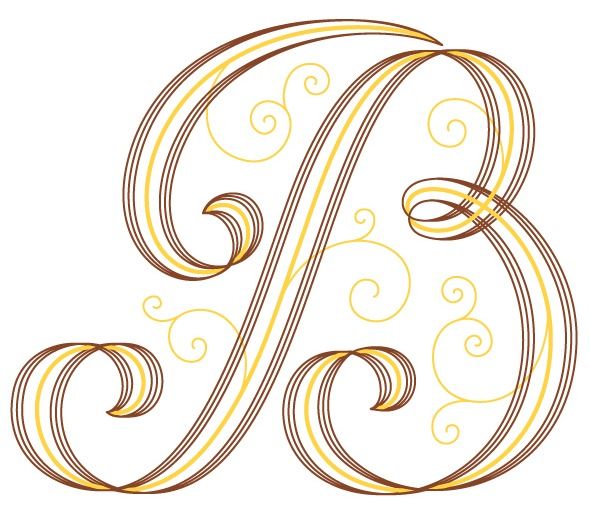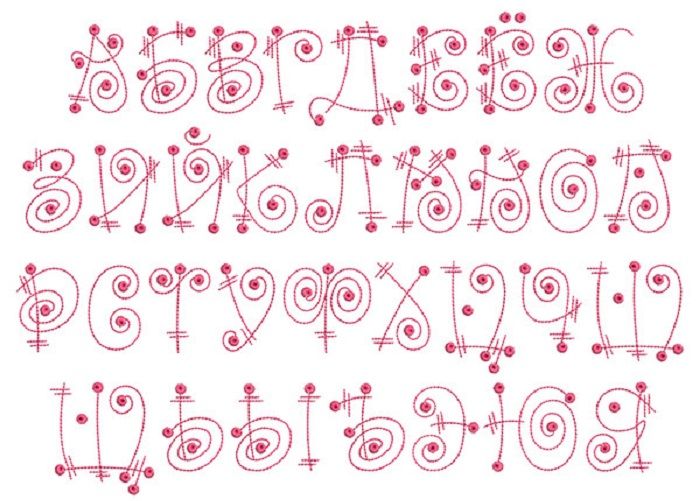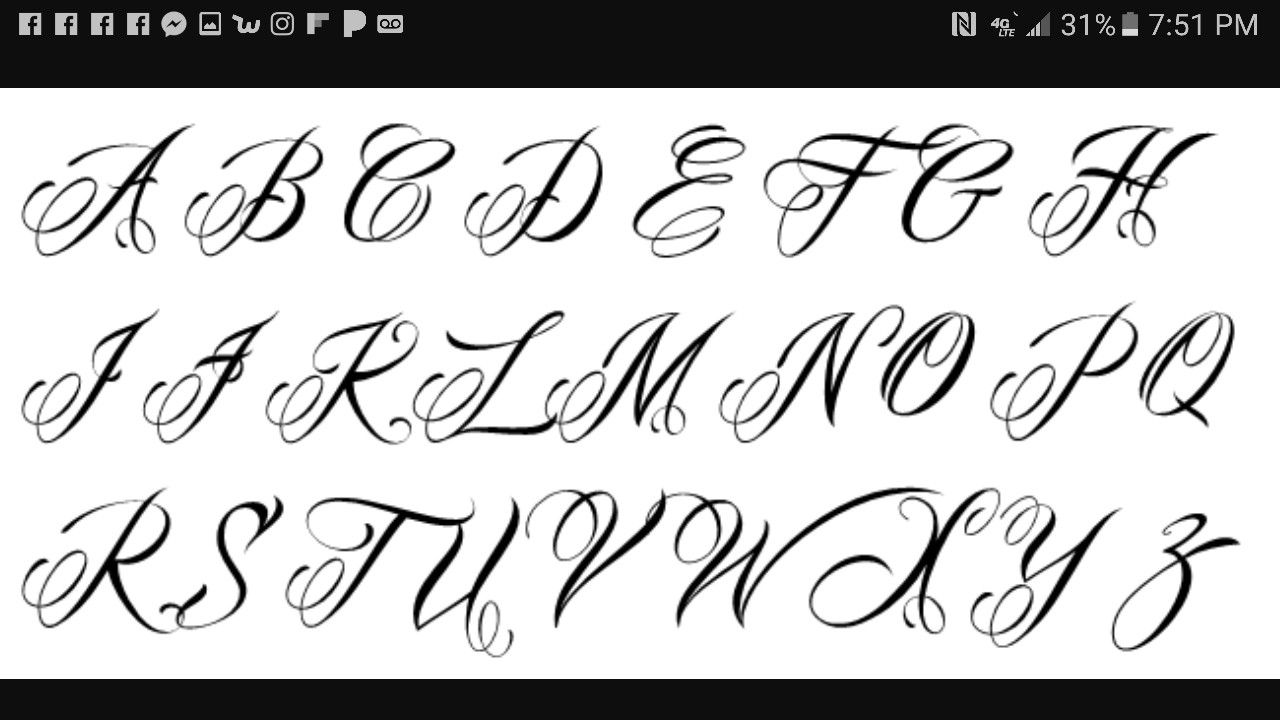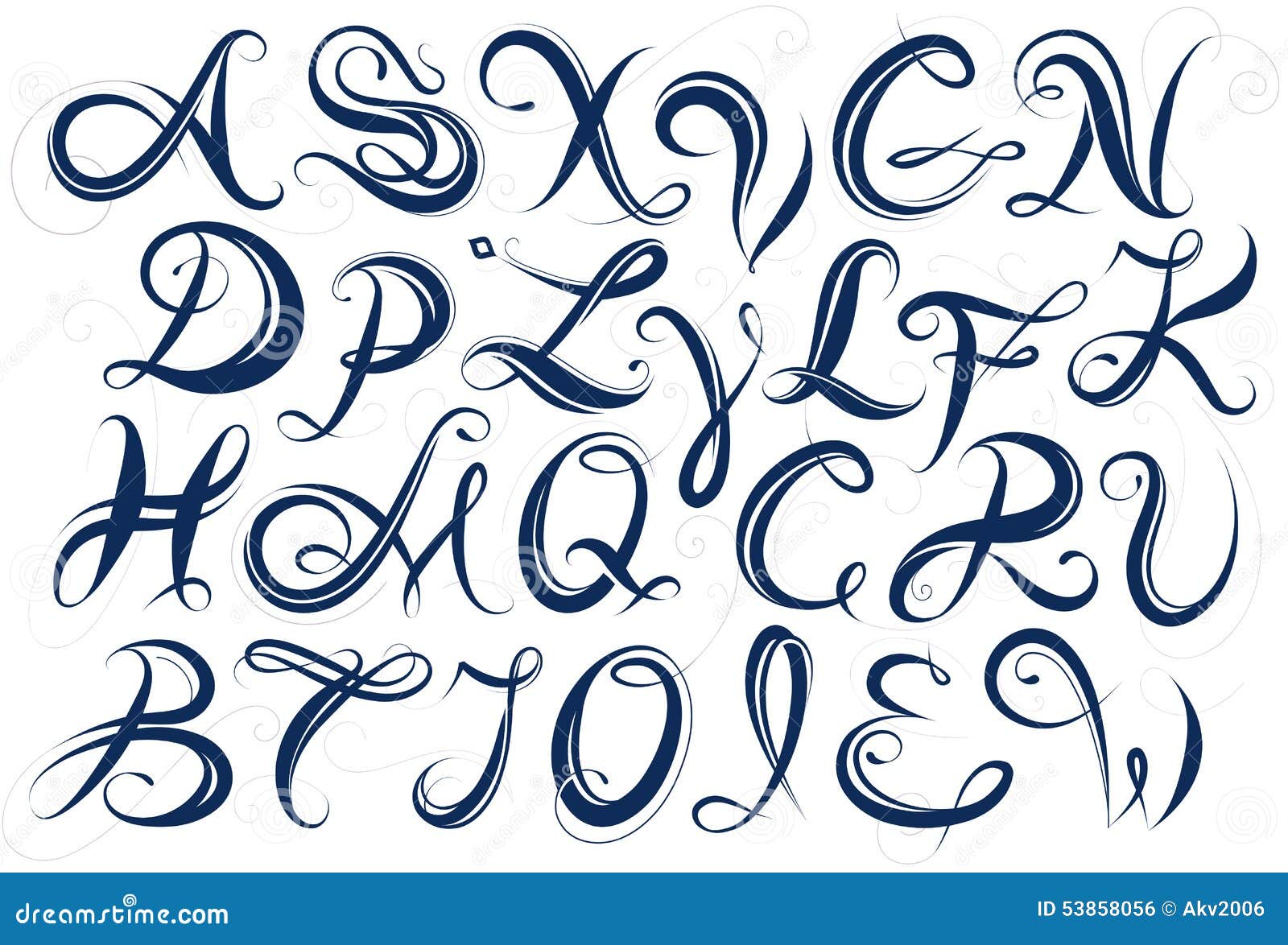
ИСКУССТВО ПЕРВОЙ БУКВЫ | Наука и жизнь
Книжный термин «инициал» происходит от латинского слова «initialis», что в переводе означает «начальный». Так называют заглавную букву увеличенного размера, с которой начинается текст книги, главы или отдельный абзац. В русской традиции инициал чаще всего именуют буквицей. Буквица может быть шрифтовой или декорированной, одноцветной или красочной, но, как бы она ни была исполнена, первое и главное её назначение — привлечь внимание читателя к началу текста. Графически буквица напоминает птичье гнездо в кроне дерева весенней порой — даже издалека глаз легко различает его в сплетении ветвей. И как гнездо украшает и оживляет дерево, так и инициальная буква украшает и оживляет собой начальную страницу. Это второе и, пожалуй, не менее важное свойство инициала: выполненный со вкусом и тактом, он радует глаз.Наука и жизнь // Иллюстрации
ПЕРОМ И КИСТЬЮ
История украшения начальных букв насчитывает более полутора тысяч лет.
Самые древние
инициалы обнаружены в античной рукописи сочинений Вергилия конца IV — начала V
века, от которой сохранились считанные листы. Большие красочные литеры в начале
каждой страницы художник составил из геометрических фигур наподобие мозаики.
Едва ли до нас дошёл первый опыт подобного рода. В названные века, видимо, уже бытовала традиция выделять начало текста, создавая торжественное вступление в книгу. Однако листать календарь назад, отодвигая дату рождения инициала в глубь веков, особой причины нет. Он появился в книге именно тогда, когда и следовало ему появиться — на излёте античности, в преддверии грядущего Средневековья. Одна великая эпоха сменялась другой: уходило в прошлое слово звучащее, искусство ораторов и певцов-аэдов — наступали, по словам С. С. Аверинцева, «времена писцов как хранителей культуры и Писания как ориентира жизни… времена трепетного преклонения перед святыней пергамена и букв».
В те годы книга уже приняла форму кодекса — стопки сшитых друг с другом тетрадей.
Их изготавливали из тщательно выделанной кожи — пергамена, который пришёл на смену ломкому папирусу. Он и служил много дольше папируса, и краски впитывал хорошо, а допущенную в слове или рисунке ошибку легко было исправить, соскоблив её ножичком.
Дойдя до последней страницы, скриптор (лат. scriptor — писец) возвращался в начало рукописи, окунал тростниковое перо в рожок с цветными чернилами и «с любовью и тщанием» вносил в начало текстовых столбцов пропущенные им заглавные буквы. Их начертание он копировал с книги, служившей ему образцом, или полагался на собственный талант каллиграфа. Позднее эту работу — прорисовку и расцвечивание инициалов и вписывание заголовков (рубрик) — в книжных мастерских стали выполнять особые художники: иллюминатор (от лат. illumino — украшаю) и рубрикатор (от лат. ruber — красный).
Чаще других для украшения чёрного текста употреблялись именно красные чернила, так называемый миний (латинское название сурика). Это несложное сочетание цветов нередко используется и ныне.
С красным цветом, кстати, связано и раннее название инициала —миниатюра, переводимое как «рисованный минием». Пройдут столетия, прежде чем это слово станет обозначать любое живописное изображение малого размера и тонкой работы.
Помимо красной в обиходе античных и средневековых писцов имелись синяя, жёлтая и зелёная краски, богатые оттенками. Для письма по цветному фону применялись белила. В роскошных манускриптах на исполнение инициалов шло творёное (растёртое в порошок) золото, реже — серебро. С благой целью сделать книгу дешевле сочинялись многочисленные рецепты для замены драгоценных металлов: толкли мелко-намелко хрусталь, ртуть смешивали с уксусом, рыбьим клеем и тальком… Однако со временем такой суррогат обесцвечивался или, что ещё печальней, проедал пергаменную страницу насквозь.
В целом же краски дошедших до нас инициалов и по сей день полны нежности и света, словно нанесены они не столетия назад. Завидная их сохранность объясняется тем, что большую часть времени книги пребывали в закрытом и даже застёгнутом виде, страницы были недоступны солнечным лучам и пыли, а чтобы пергамен не грызли мыши, писцы добавляли в чернила полынную настойку.
Заглавные буквы в начале текста, на первых порах просто выделяемые цветом, от книги к книге росли в размерах, выступали за край строки, украшались плетением и фигурками животных. Неискушённому взгляду может показаться, что персонажи этих рисунков случайны и внесены художником в текст для забавы — настолько они порой далеки от его содержания. Но на деле средневековый мастер уделял смыслу нисколько не меньше внимания, чем, скажем, цветовому равновесию или композиционной завершённости своей работы.
Для убранства ранних европейских книг характерно обилие христианских символов, ныне достаточно подзабытых.
Для читателя средневекового, напротив, это привычные, повседневные знаки. Обращённые больше к разуму, чем к чувствам, они были своеобразной знакописью, живым наследием первых веков христианства, выработавшего свой изобразительный язык в мозаиках и фресках катакомб. Язык, в котором за внешне простыми рисунками скрывалась более глубокая реальность, и, чтобы проникнуть в неё, необходимо быть посвящённым.